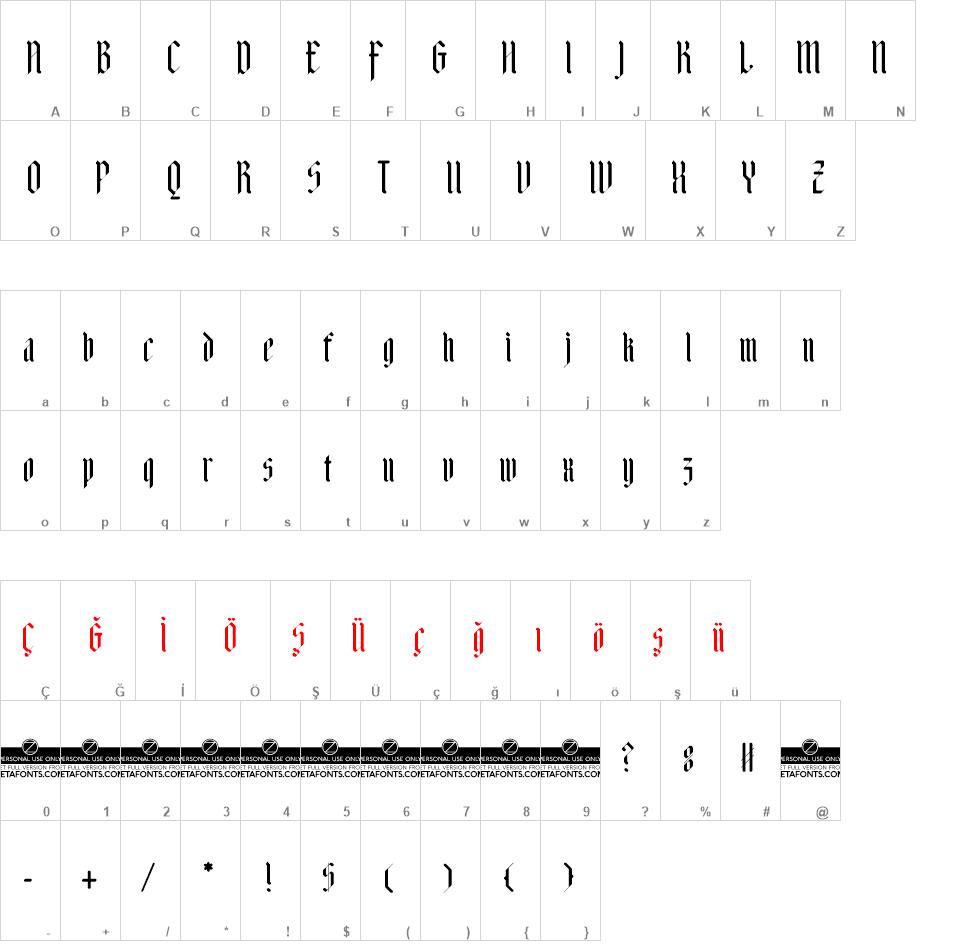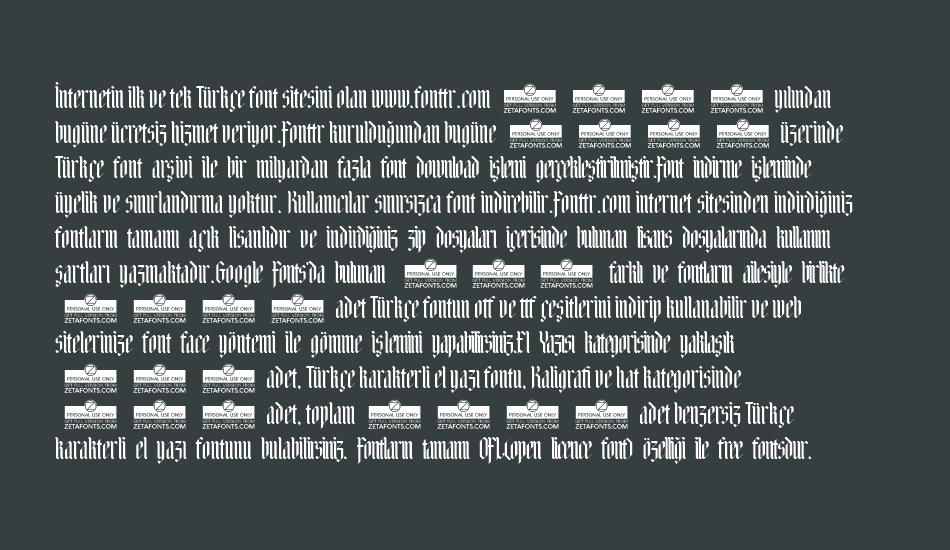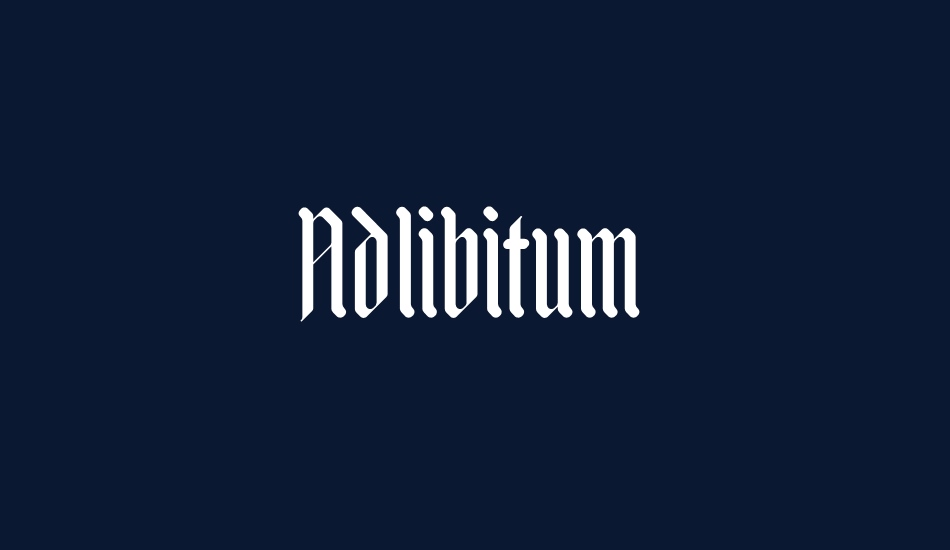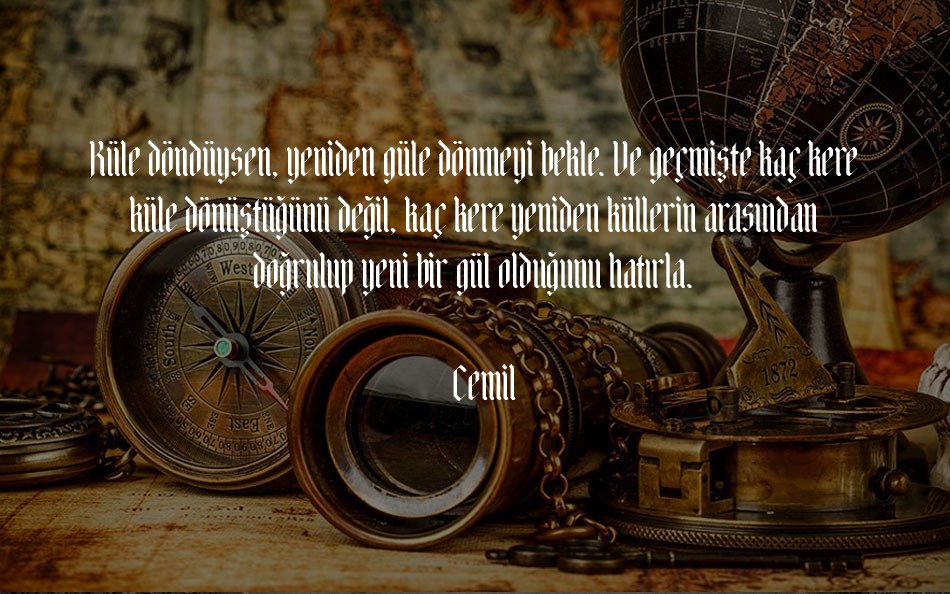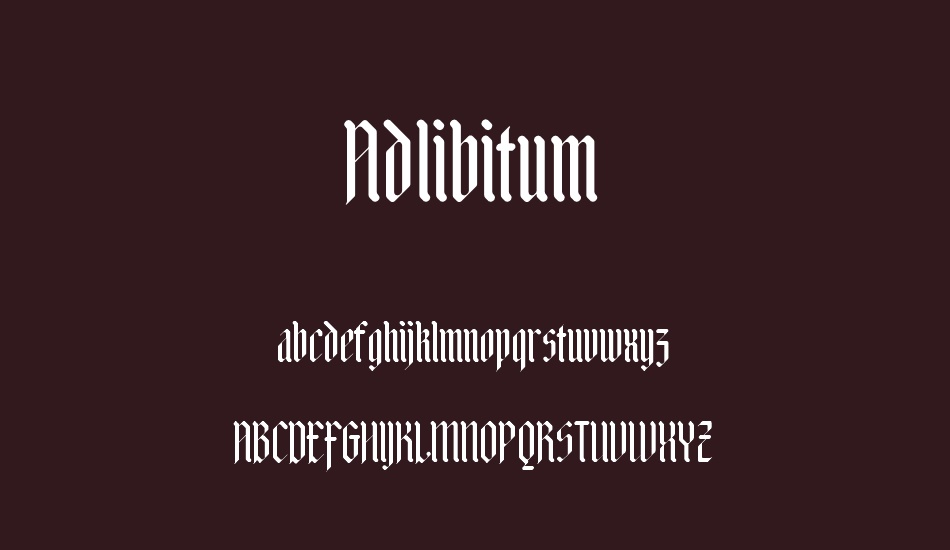
Adlibitum Font Family font
Francesco Canovaro tarafından tasarlanan Adlibitum, eski textura medioeval komut karakterlerinin çağdaş bir restyls olarak tasarlanmış bir yazı tipi biçimidir. 45 derecelik açılar ve yumuşak yuvarlak köşeleri ile güçlü bir dikey aksan ve geometrik bir tasarıma sahiptir. Üç ağırlıkta ve Avrupa dilleri için desteklenen geniş bir karakter kümesi ve harfler için açık tip destek sunuyor.